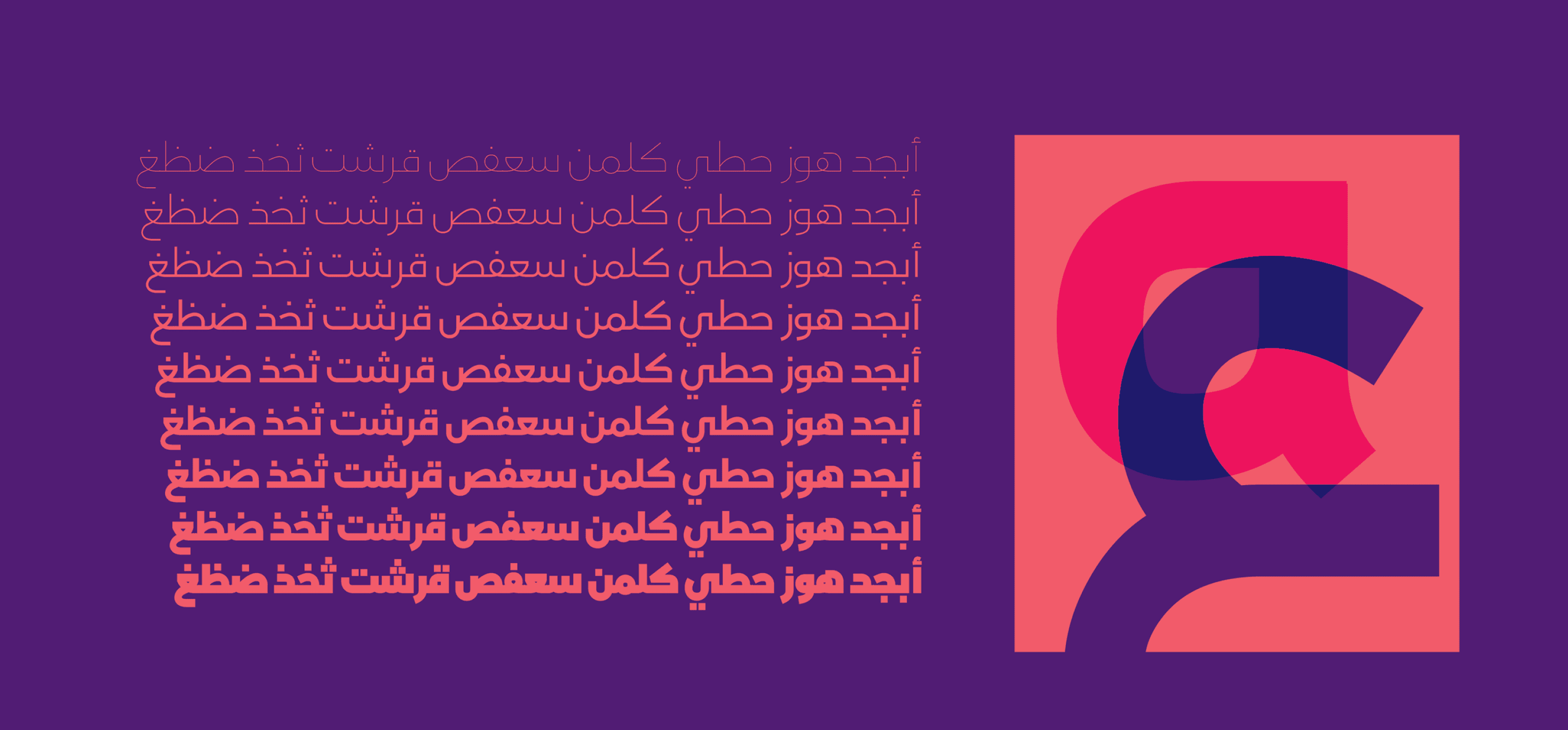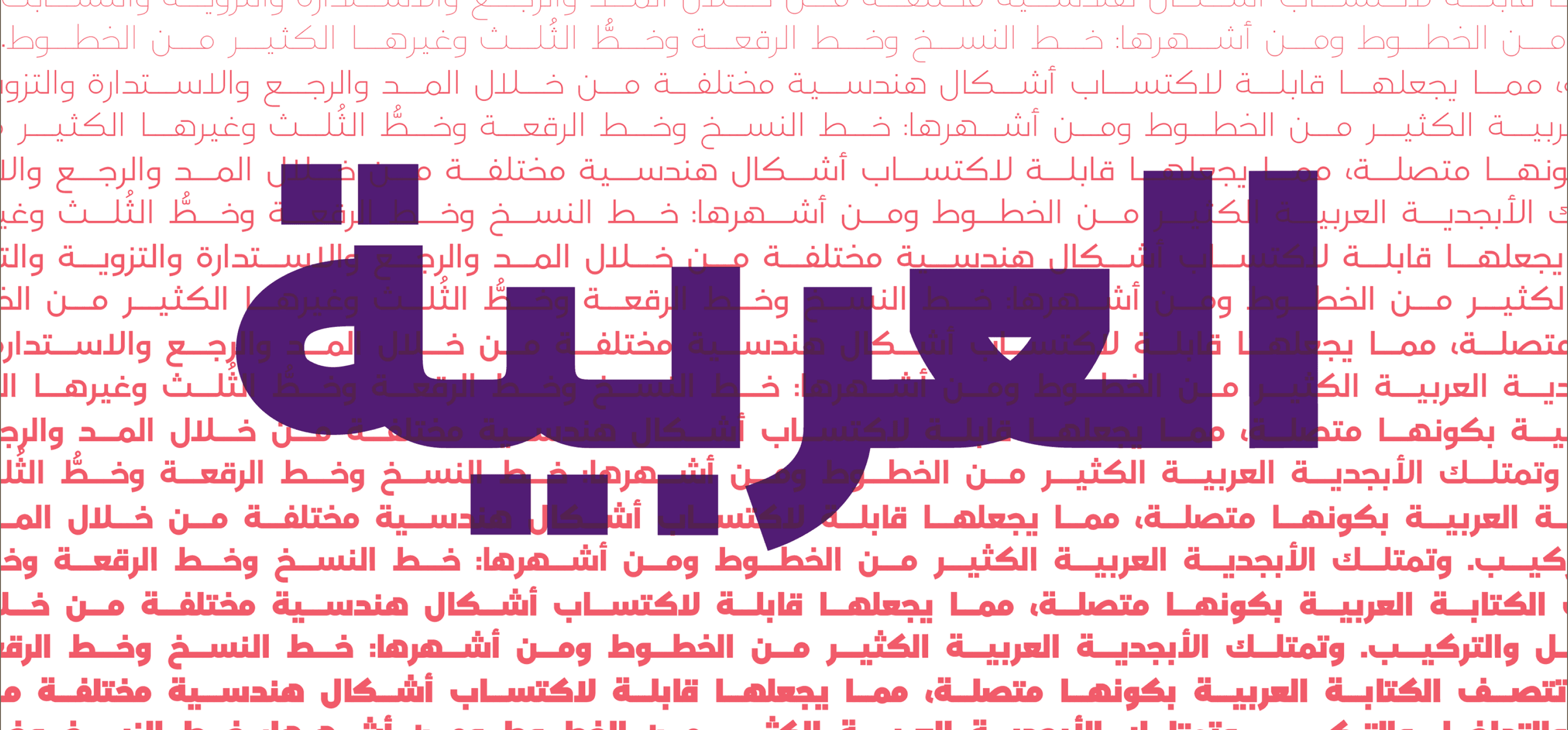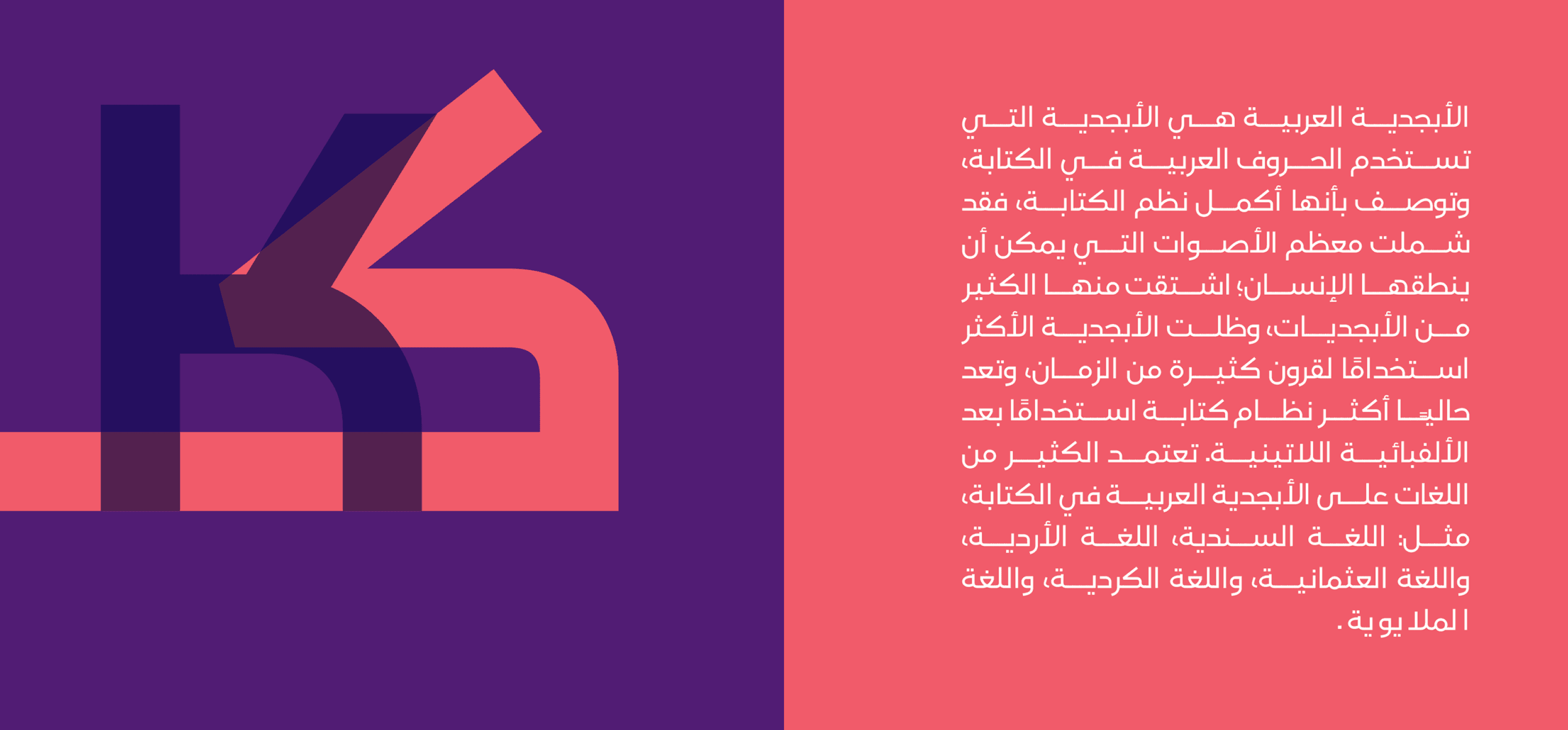
بلقيس برو هو خط حديث باللغتين العربية واللاتينية ينتمي إلى عائلة الخط الكوفي. وتتميّز هذه النسخة بتحسينات في أشكال الحروف، بالإضافة إلى العديد من الإضافات التي تجعله مناسبًا لاستخدامات متنوعة.